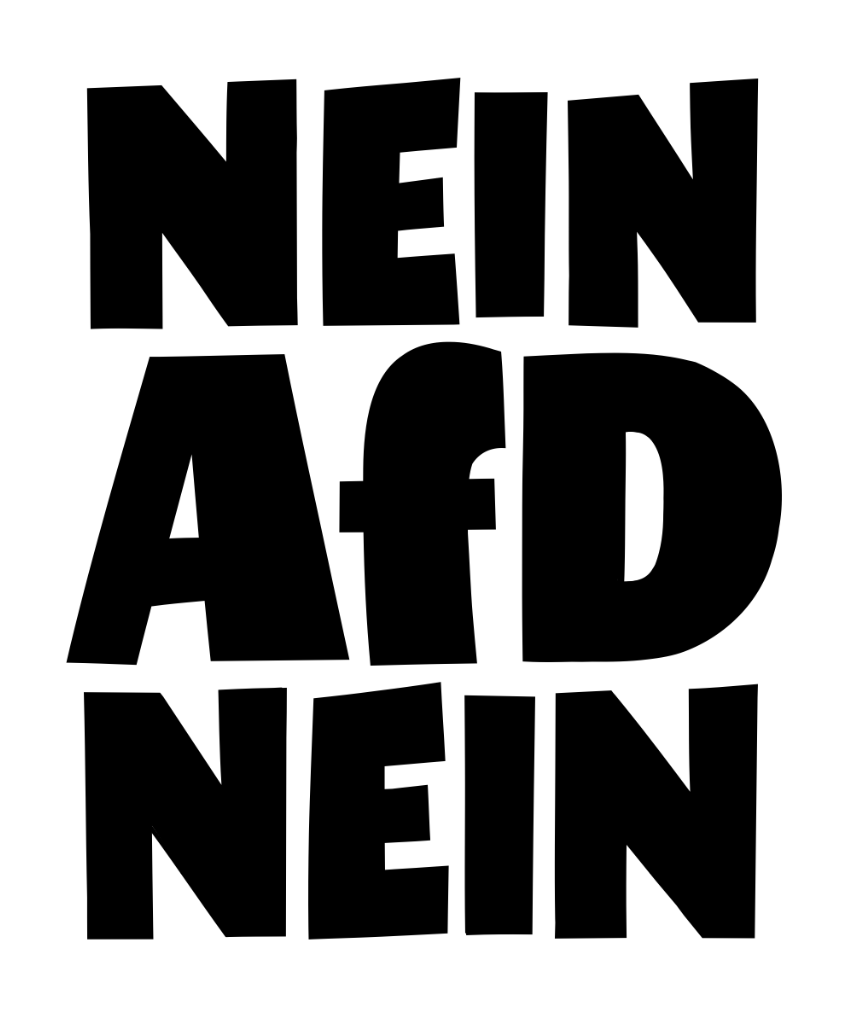
Als im Januar 2024 die Correctiv-Recherchen erschienen, bin ich mit ein paar Anti-AfD-Schildern auf die große Demo in Hamburg gegangen. Über die sozialen Medien fanden meine Schilder deutschlandweit Nachahmer*innen und haben Menschen inspiriert, selbst Flagge zu zeigen.
Dies ist die Geschichte, wie ich wurde zur Demoschild-Influencerin wurde.
Das analoge Gif für den CSD war der Vorläufer für das, was mir seit Januar 2024 passiert ist.
Ich meinte eigentlich »Ja, muss sein.« als Antwort auf die Frage, die queeren Menschen immer wieder gestellt wird »Muss das denn sein?« (»dass ihr so laut seid, dass ihr so bunt seid, dass ihr eine Parade macht, dass ihr ständig allen erzählt, dass ihr schwul seid«).
Dass ich das Komma vergessen habe, machte das Schild aber einem größeren Publikum zugänglich, denn viele dachten, es ginge um gegenseitiges Einvernehmen, im Sinne von consent: »Ein »Ja« muss ein«. Auch gut.
Am 10. Januar veröffentlichte das Correctiv seine Recherchen zum Geheimtreffen von Rechtsradikalen zur sogenannten »Remigration«.
Zwanzig Millionen Menschen deportieren, nur weil euch ihre Haarfarbe nicht passt – sag mal spinnt ihr?!
Zur ersten Demo in Hamburg am 12.1. kamen 2500 Leute. Hamburg hat fast zwei Millionen Einwohner*innen – wo waren die alle?!
Für die nächste Demo, eine Woche später, habe ich ein Schild gemalt. Ich mag Sprache und deswegen mag ich keine abgedroschenen Phrasen und Parolen wie »Nazis raus«. Also habe ich auf mein Schild einfach »Nein AfD Nein« geschrieben.
Und weil die Bedrohung durch die extreme Rechte ernst genug ist, habe ich noch zwei weitere Schilder gemalt, um das Ganze aufzulockern. Ich dachte: »Die Leute wollen eigentlich auf dem Sofa sitzen und ihre Ruhe haben statt auf eine Demo zu gehen, also soll es wenigstens ein bisschen Spaß machen.« Auf meinen Zusatzschildern stand »echt nicht« und »könnta knicken«.
Mit diesen Schildern ging ich am 19. Januar 2024 auf die Demo am Jungfernstieg. Die Demonstration musste abgebrochen werden, weil sie sie so überfüllt war. Zuerst war von 50.000 Teilnehmer*innen die Rede, diese Zahl wurde jedoch Anfang Februar 2024 von der Hamburger Innenbehörde deutlich nach oben korrigiert – auf mehr als das Dreifache: 180.000 Menschen gegen Nazis.
Demoschild in Elmshorn – beeindruckend gut nachempfunden.
Am Rande dieser Demo machte der PR-Berater und Influencer Marc Raschke im Vorbeigehen ein Foto von mir und meinen Schildern und zeigte es in seinen Stories auf Instagram zeigte.
Marc Raschke hat über 100.000 Follower*innen, seine Story haben anscheinend viele Leute gesehen, denn eine Woche später schickte mir eine Freundin ein Foto von einer Demonstration in einer Kleinstadt bei Hamburg. In Elmshorn trug eine Frau eine Kopie meiner Schilder bei sich. Meine Freundin fragte sie, woher sie das habe und sie sagte: »Ach, das hab ich irgendwo im Internet gesehen …«
Gleichzeitig haben andere Leute meine Schilder auch nachgemalt und mir von ihren Versionen Fotos geschickt. Es gab weitere Demos, ich habe weitere Schilder gemalt und dabei festgestellt, wie viele Wörter sich auf D reimen: »AfD? Scheiß Idee«, »AfD? Alter nee!«, »AfD is so passé«
Diese Schilder haben wieder Leute als Vorlage für ihre eigenen verwendet, Kolleg*innen haben meine Schilder in ihren Zeichnungen aufgegriffen, und der Stil wurde auch für andere Zwecke übernommen: zum Beispiel für den Kampf zur Rettung eines öffentlichen Bades in einer Kleinstadt in Niedersachsen.
Protestieren auf dem Hamburger Michel
Viele Wörter reimen sich auf »D«.
Demoschild-Zeichnung von Tanja Esch
Mein Original …
… und die Version von Katharina Winter
Demoschild-Zeichnung von Heike Haas
Mein erstes Schild gegen die AfD …
… und die Version von Christoph Babbel
gezeichnete Interpretation von Franziska Walther
Das Demoschild-Tutorial finden Sie hier.
Auf Instagram folgen mir die meisten Menschen wahrscheinlich weil sie sich für Lettering und Design interessieren. Sie sind nicht unbedingt politisch. Aber ich dachte, wenn ich die Leute bei ihrem Interesse für Schrift packe, sie dazu bringe, ein Schild zu malen und auf eine Demo zu gehen – dann wäre wirklich etwas gewonnen.
Also habe ich Anfang Februar 2024 einen kostenlosen Demoschild-Workshop im Hamburger Museum für Kunst und Gewerbe organisiert und bin zwei Wochen später gemeinsam mit einigen der Teilnehmer*innen auf die nächste Demo gegangen. Aus diesem Workshop haben sich im Laufe des Jahres weitere Demoschild-Workshops ergeben.
Weil das Interesse an meinen Schildern so groß war, habe ich außerdem ein Tutorial für meinen Blog geschrieben. Und selbstverständlich habe ich aus meinem ersten Demoschild auch wieder ein Gif gemacht.